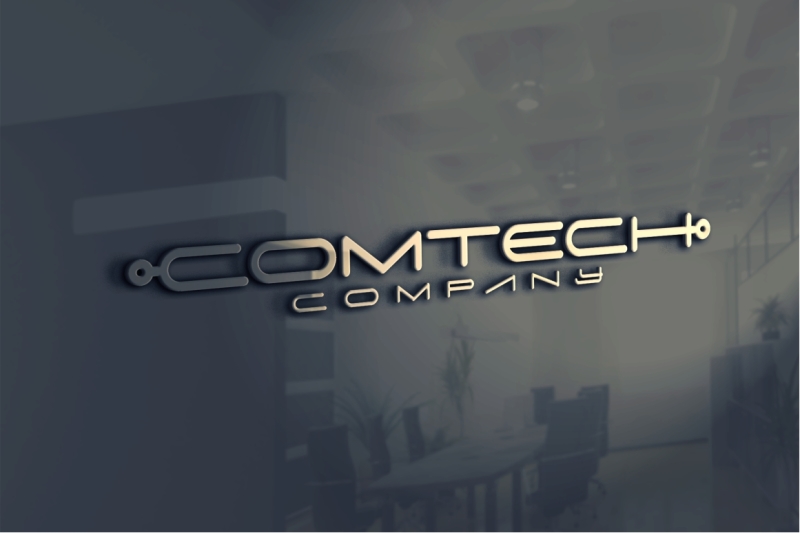
Шрифт — Techno Normal / Creativo.one
Интересный шрифт, который хорошо подходит для работы в фотошопе.
Metropolis
Metropolis by Josip Kelava обязан своим несравненным видом плакатам, сделанным в стиле арт-деко и технике двойной линии. Художник сумел объять 1920-е и правильно выразить то время. Шрифт выглядит городским, художественно-утонченным и изощренным. Он предназначен для написания на латинице и кириллице. Также шрифт включает цифры и некоторые основные знаки препинания.
Barkentina